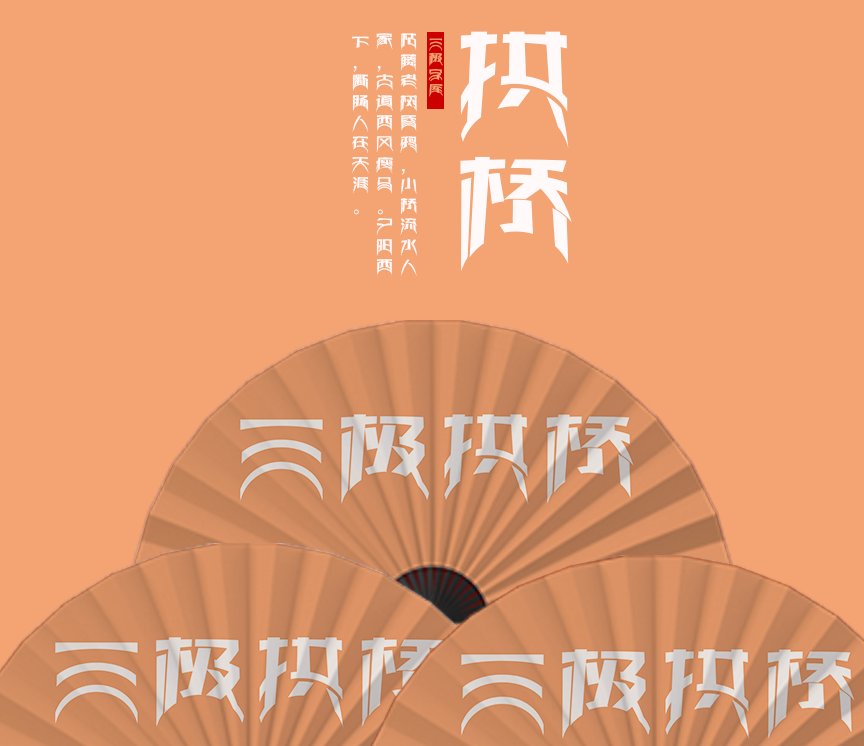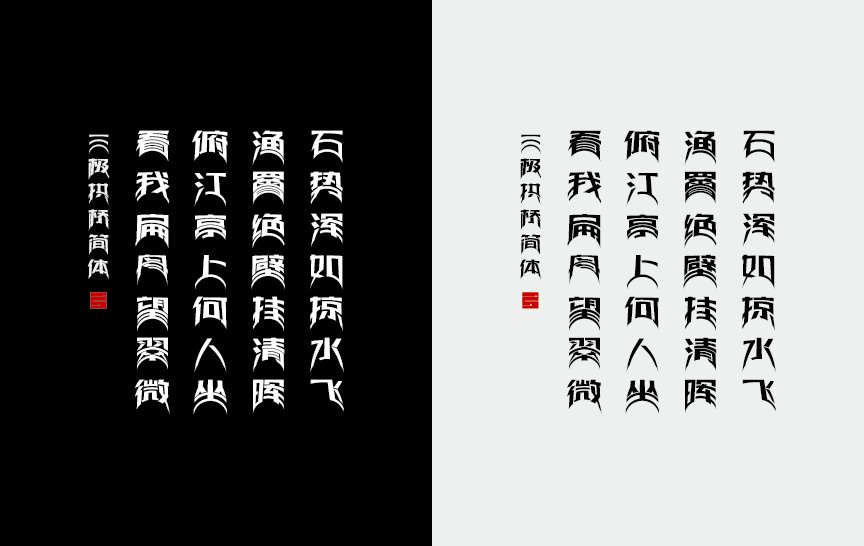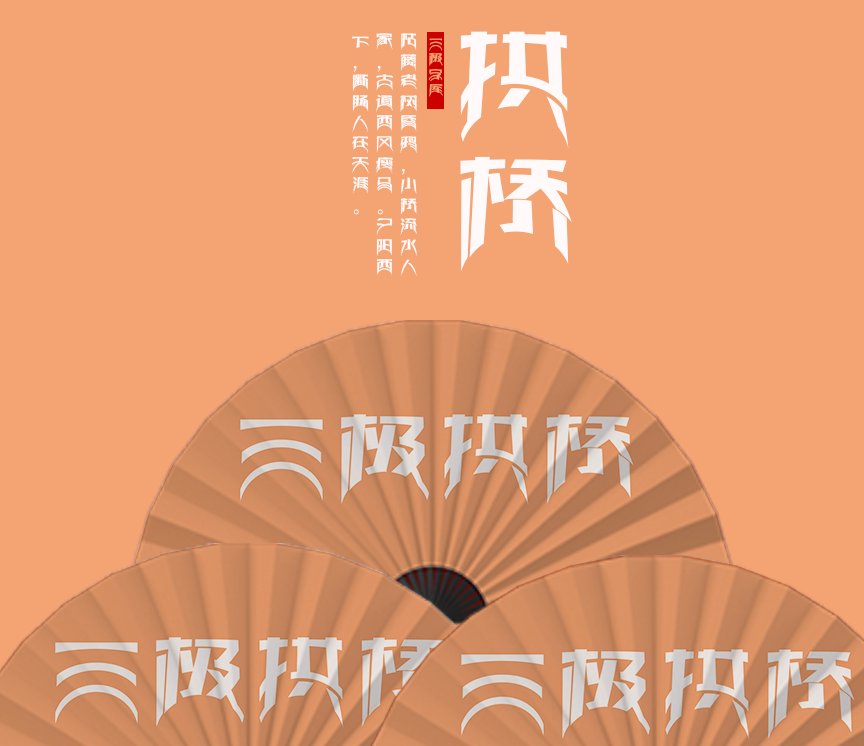
字体名称:三极拱桥简体
字体类别:混合字体
字设计师:欧伟
适用场景:杂志、书籍、广告、标志、宣传册、包装、影视、动漫、屏幕显示、交互设计。
字库简介:三极拱桥简体是一款融合了中国古代拱桥形意的创意字体。其笔画造字结构如同一座坚毅的石拱桥,上半部分字形整体结构严谨规整,下半部分字体字形弯曲如同河水流动,字形整体给人呈现出一种很强的视觉冲击效果。这款字适合于古典、文学类的包装宣传使用。